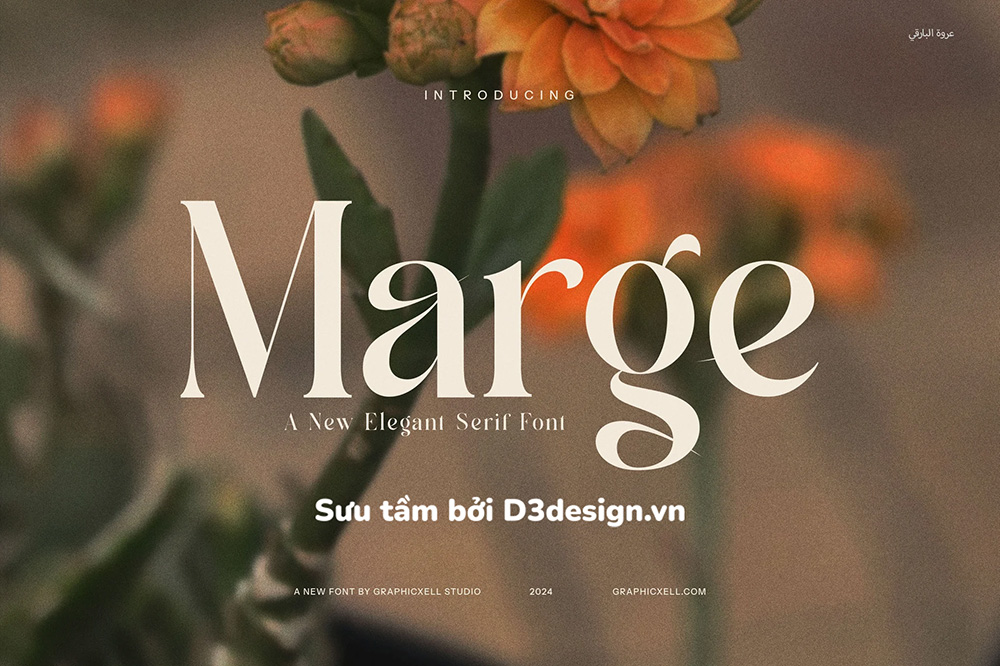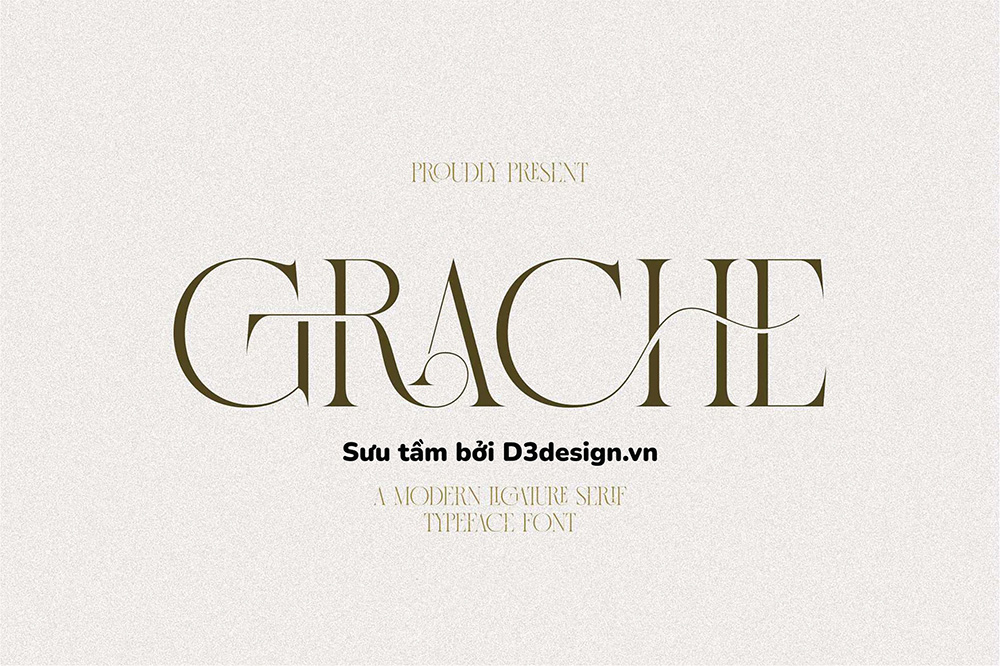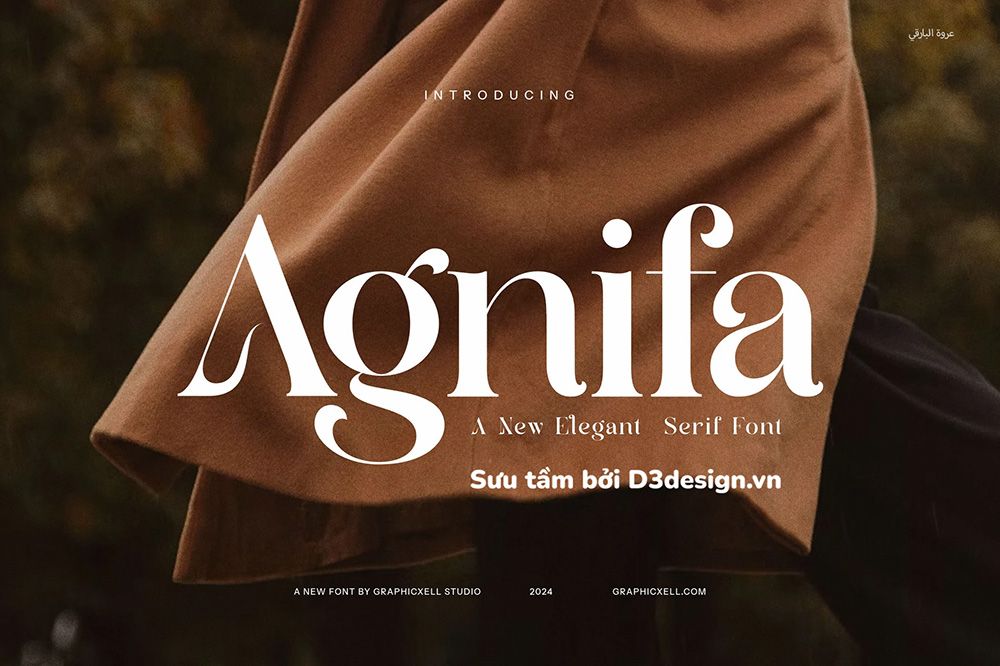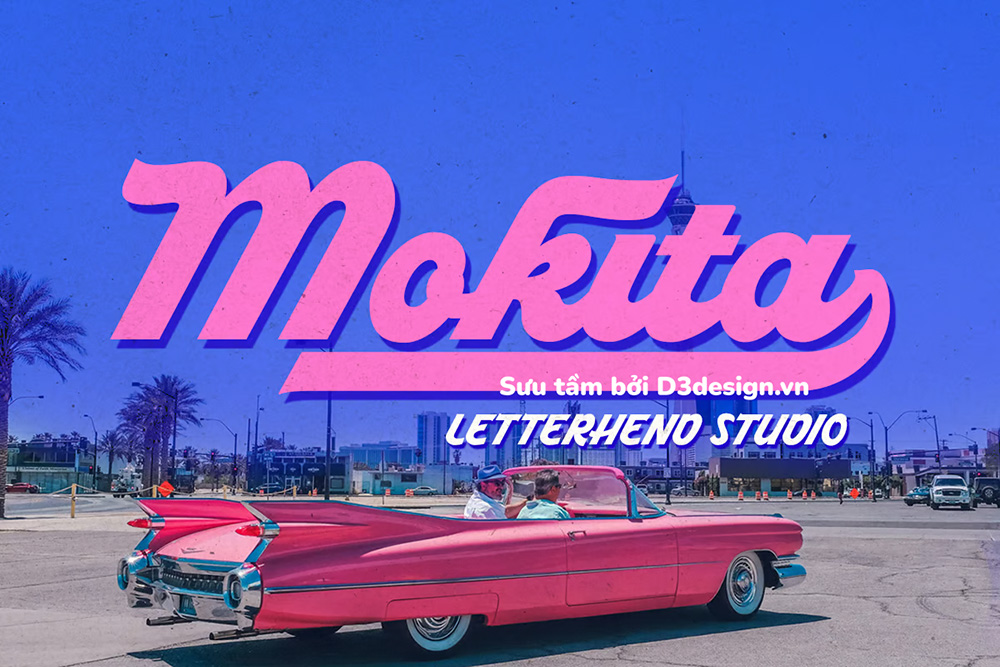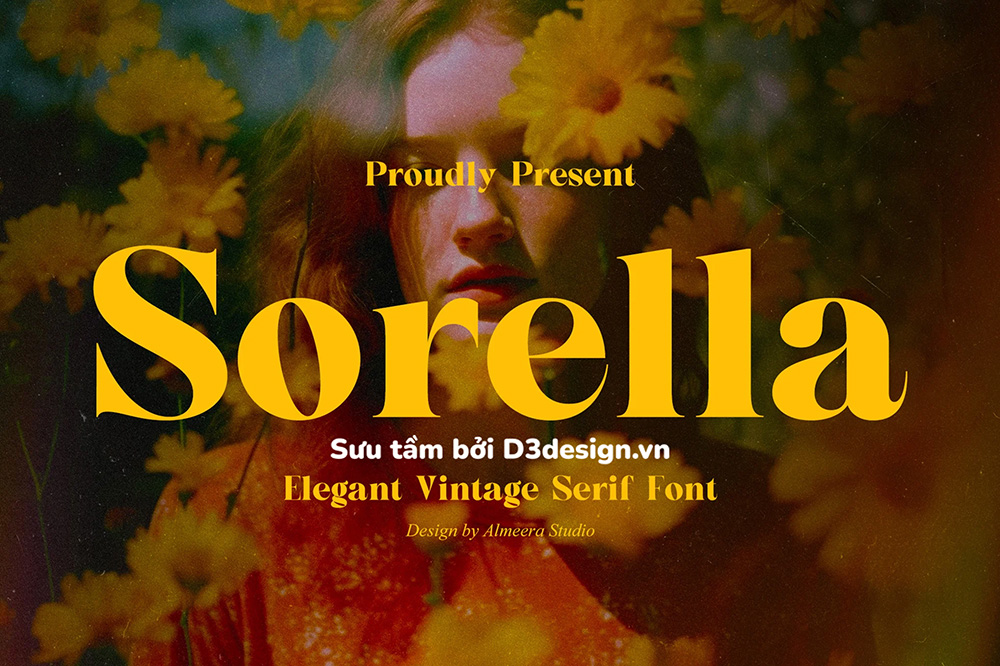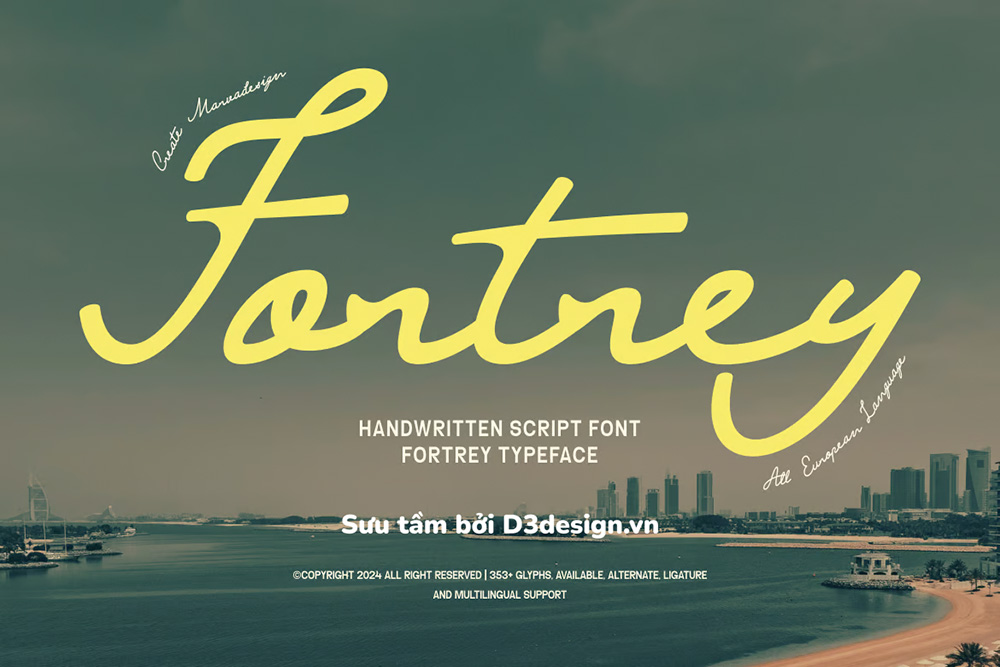
Tải 6 Font Chữ Siêu Đẹp, Hoàn Toàn Miễn Phí Dành Cho Designer 2024
Font chữ trong thiết kế là một tập hợp các ký tự bao gồm chữ cái, số và ký hiệu, được thiết kế với một kiểu dáng đồng nhất. Font chữ có vai trò quan trọng trong thiết kế vì nó ảnh hưởng đến tính thẩm mỹ và khả năng truyền đạt thông điệp của sản phẩm thiết kế.
Font chữ đóng một vai trò rất quan trọng trong thiết kế đồ họa. Dưới đây là một số lý do chính tại sao font chữ quan trọng:
Truyền tải thông điệp: Font chữ giúp truyền tải thông điệp của bạn một cách rõ ràng và chính xác. Mỗi font chữ có một phong cách riêng, và việc chọn font chữ phù hợp có thể giúp làm nổi bật thông điệp mà bạn muốn gửi đến người xem.
Tạo cảm xúc: Font chữ có thể ảnh hưởng đến cảm xúc và cảm nhận của người xem. Ví dụ, các font chữ sans-serif thường mang lại cảm giác hiện đại và sạch sẽ, trong khi các font chữ serif có thể tạo cảm giác truyền thống và lịch lãm.
Tạo sự nhất quán: Việc sử dụng font chữ nhất quán giúp tạo sự đồng nhất và chuyên nghiệp cho thương hiệu. Một hệ thống font chữ được chọn lọc và sử dụng nhất quán sẽ giúp người xem dễ dàng nhận diện và nhớ đến thương hiệu của bạn.
Tăng tính thẩm mỹ: Một thiết kế đẹp mắt cần có sự kết hợp hài hòa giữa các yếu tố, và font chữ là một trong số đó. Chọn đúng font chữ có thể làm cho thiết kế của bạn trở nên hấp dẫn và thu hút hơn.
Tăng khả năng đọc: Font chữ phù hợp giúp tăng khả năng đọc của văn bản, đặc biệt là trên các phương tiện kỹ thuật số. Một font chữ dễ đọc sẽ giúp người xem tiếp nhận thông tin một cách dễ dàng và nhanh chóng hơn.
Phân cấp thông tin: Font chữ có thể giúp phân cấp thông tin một cách hiệu quả. Sử dụng các kích thước và kiểu font khác nhau có thể giúp người xem dễ dàng nhận biết và hiểu được cấu trúc thông tin của thiết kế.
Tóm lại, font chữ không chỉ là yếu tố trang trí mà còn đóng vai trò quan trọng trong việc truyền tải thông điệp, tạo cảm xúc và tăng tính thẩm mỹ cho thiết kế đồ họa. Việc chọn lựa và sử dụng font chữ một cách thông minh có thể làm nên sự khác biệt lớn cho bất kỳ dự án thiết kế nào.